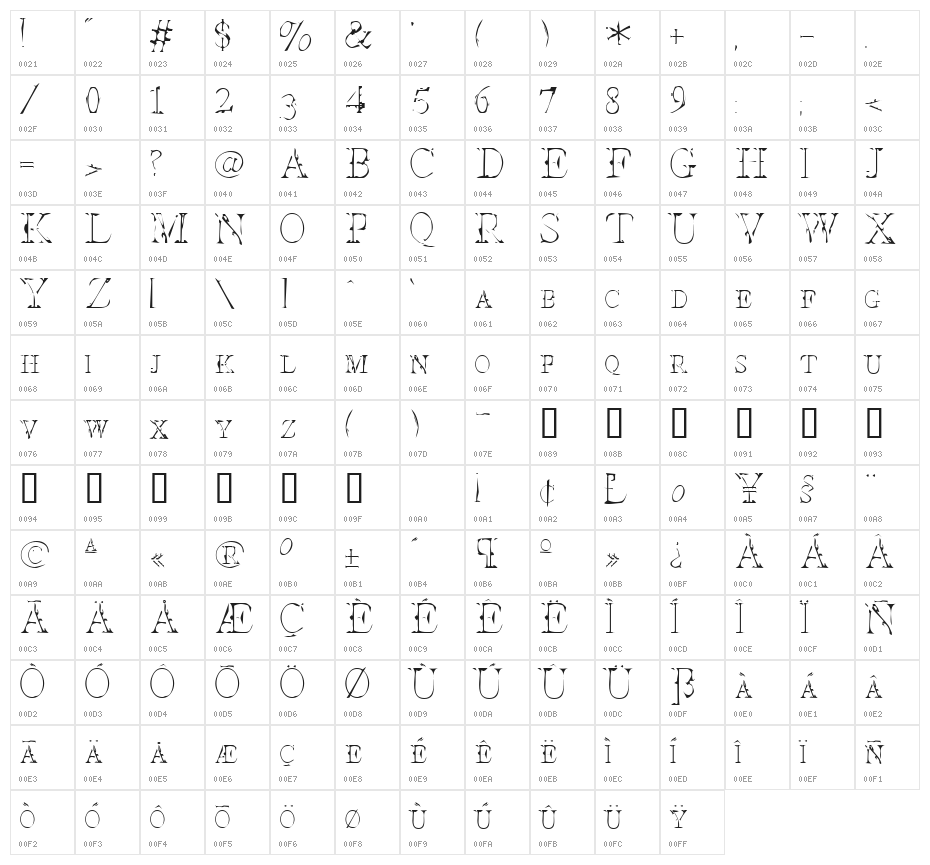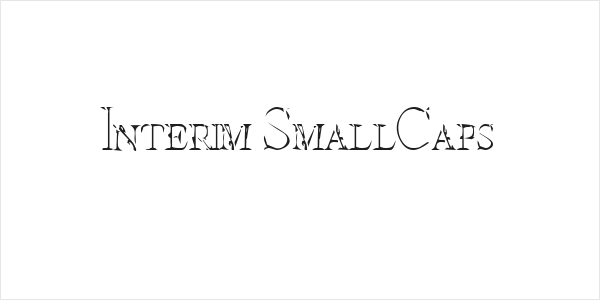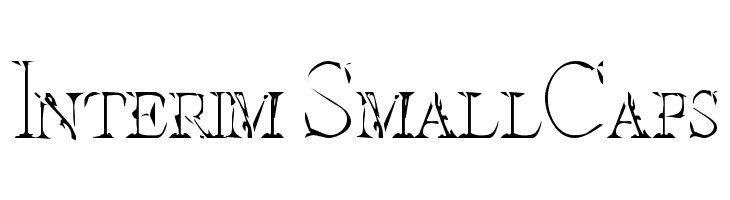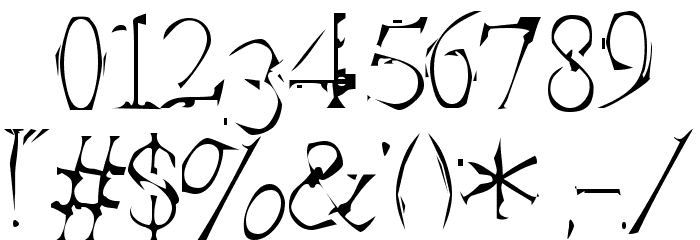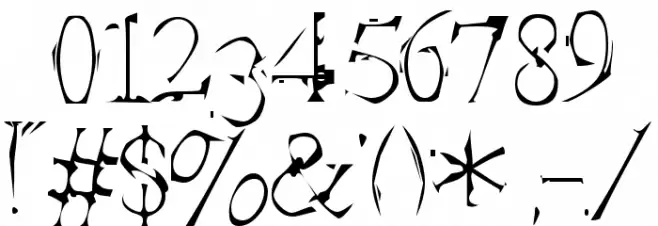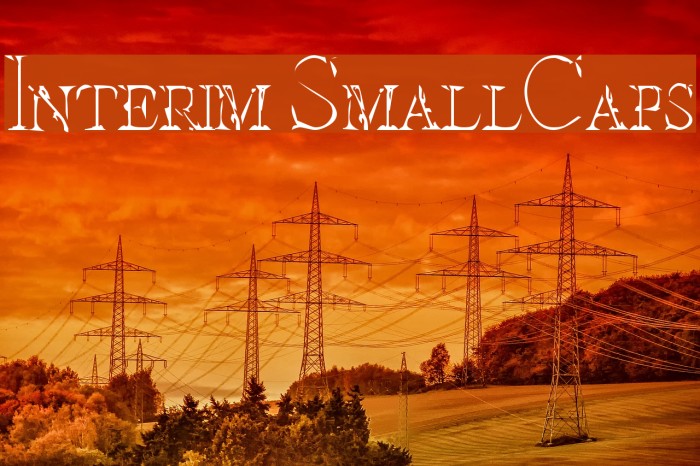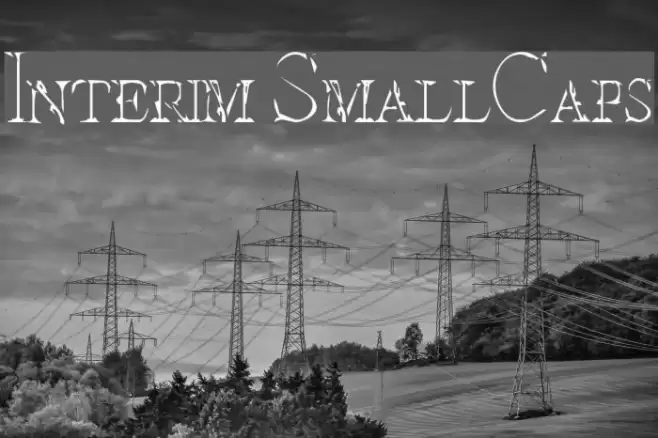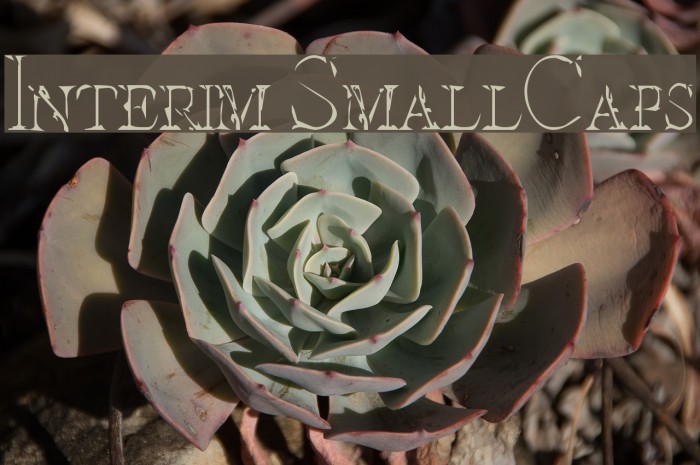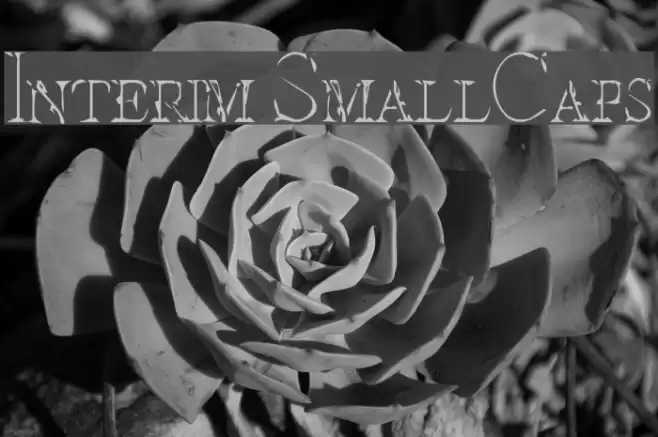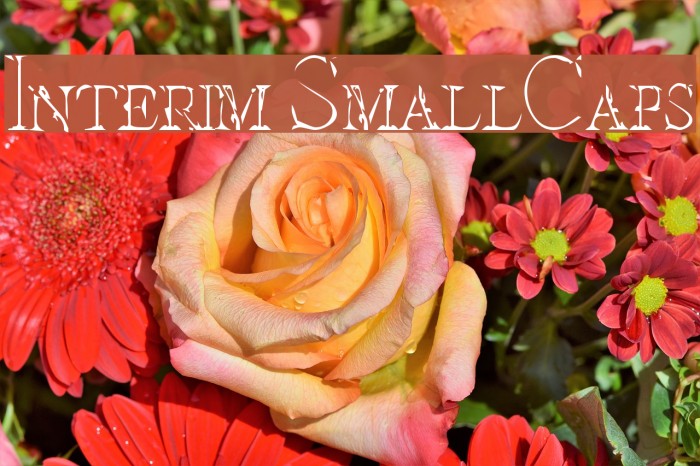
Interim SmallCaps Font
| Vorgeschlagene Projekte | Ideal for album covers, posters, branding for edgy or alternative products, and any design needing a bold, artistic touch. |